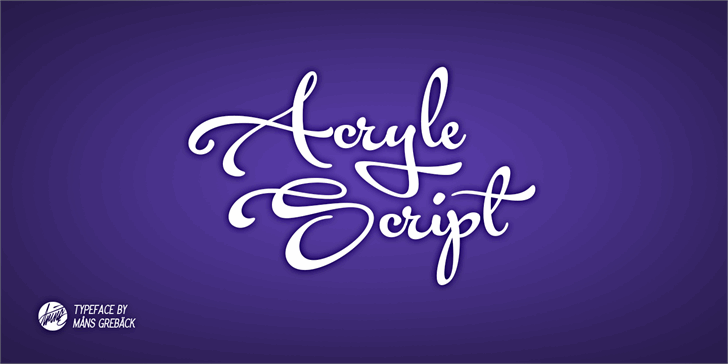
A Acryle Script é uma fonte script criada pelo designer Hamilton, conhecida por seu estilo fluido e elegante. Suas linhas fluidas e suas curvas suaves remetem a um estilo de escrita fluida que pode ser encontrado no século XIX ou até mesmo no século XVIII. Compostas em 524 caracteres, a fonte oferece uma ótima solução para qualquer projeto que busque o charme elegante dos tempos passados. A Acryle Script é perfeita para editoriais de moda, revistas culturais e até mesmo em design gráfico vintage. Visite o site da Mansgreback para comprar uma licença comercial desta fonte única.